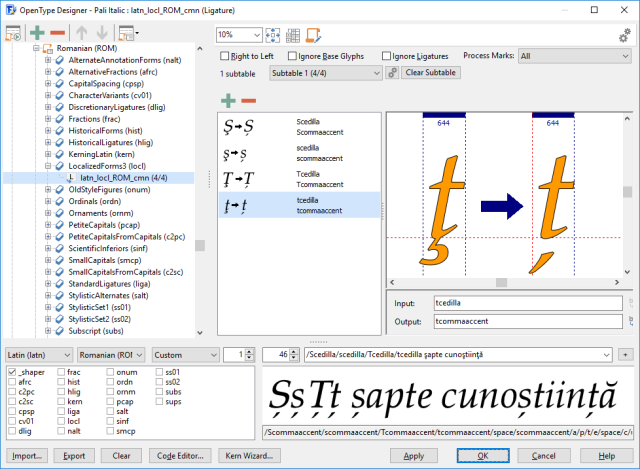
罗马尼亚语使用带逗号变音符的 S/s 与 T/t。出于历史遗留原因,部分文本和/或字体错误地使用了带 cedilla 的 S/s 与 T/t。
罗马尼亚语使用带有逗号重音的 S/s 和 T/t。由于遗留原因,尽管建议从软音符迁移到逗号,但许多罗马尼亚语文本和一些字体错误地使用 S/s 和 T/t 软音符。此功能为罗马尼亚语和摩尔多瓦语替换逗号重音变体。
常规的小型大写字母和小型大写字母功能不考虑这些规则,会将常规小写 i 更改为无点的大写 I,因此对土耳其语失败。在这种情况下,可以使用本地化形式来修复此语言特定问题。
您可以使用 FontCreator 轻松地向字体添加本地化形式功能。首先确保您的字体包含所需的字符。如果您使用了名为东欧的转换脚本,您的字体已经包含它们。如果没有,请运行字形转换脚本,或通过插入字形对话框手动添加缺失的字形。
Scedilla, scedilla, Tcedilla, tcedilla, Scommaaccent, scommaaccent, Tcommaaccent, tcommaaccent
接下来,转到 OpenType 设计器并单击左上角的工具栏项。确保选中常用本地化形式选项。
OpenType 功能和查找现在已添加到您的字体中,如上所示。摩尔多瓦方言是罗马尼亚语的几种方言之一,也存在相同问题,因此也得到了处理。
您可以输入预览文本来测试您的功能。确保您选择了拉丁脚本和罗马尼亚语言并启用了 _shaper 或 locl 功能。您可以输入字母或斜杠后跟字母的字形名称。
/Scedilla/scedilla/Tcedilla/tcedilla şapte cunoştiinţă